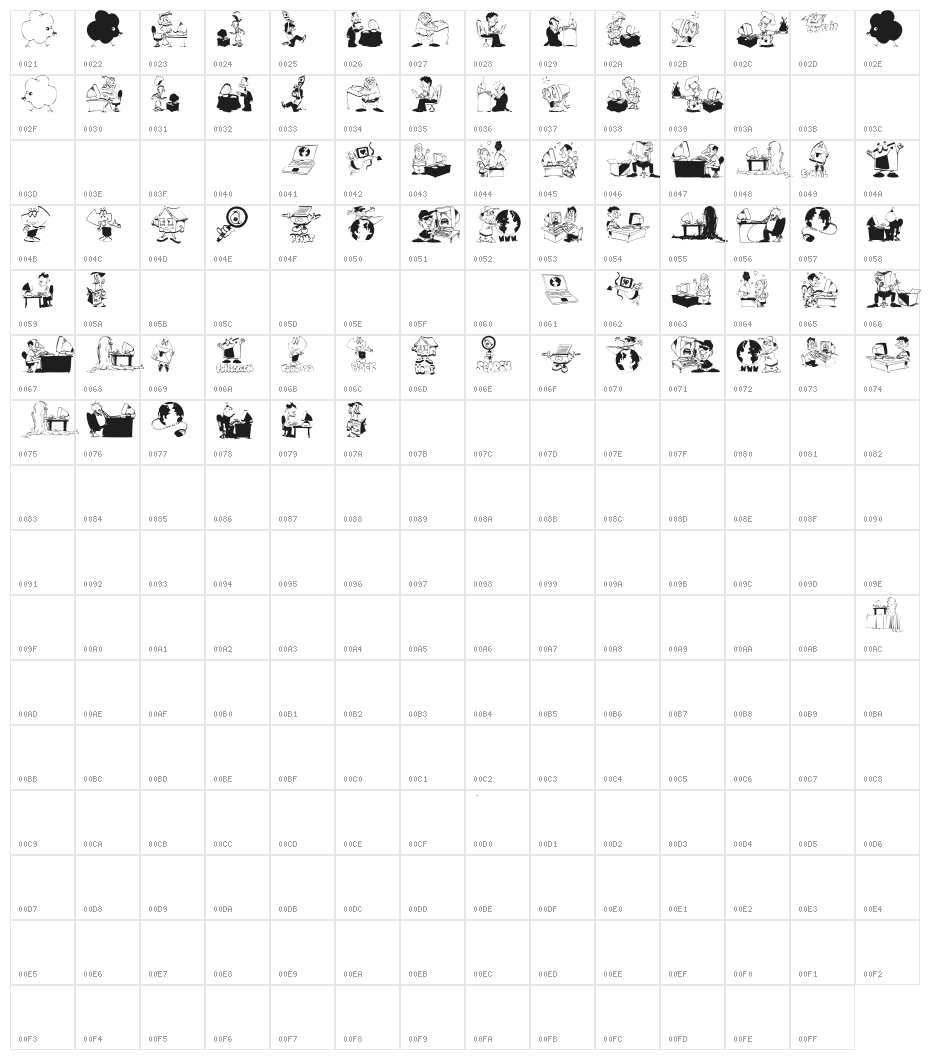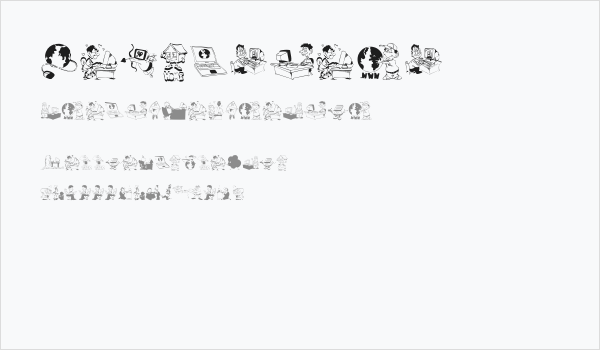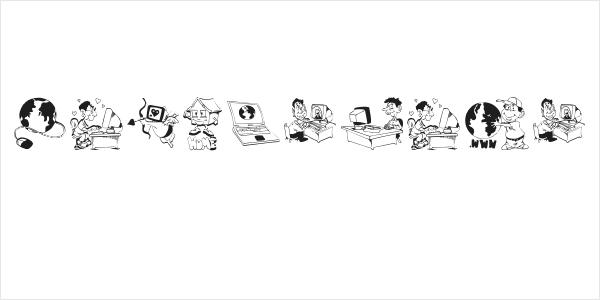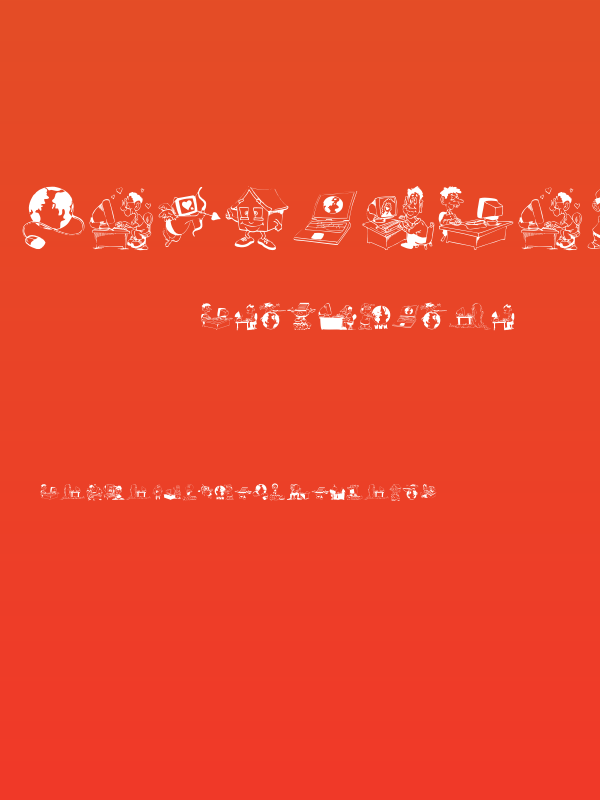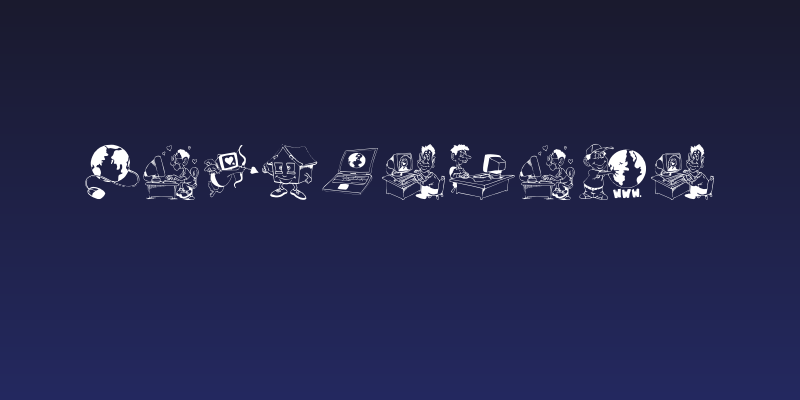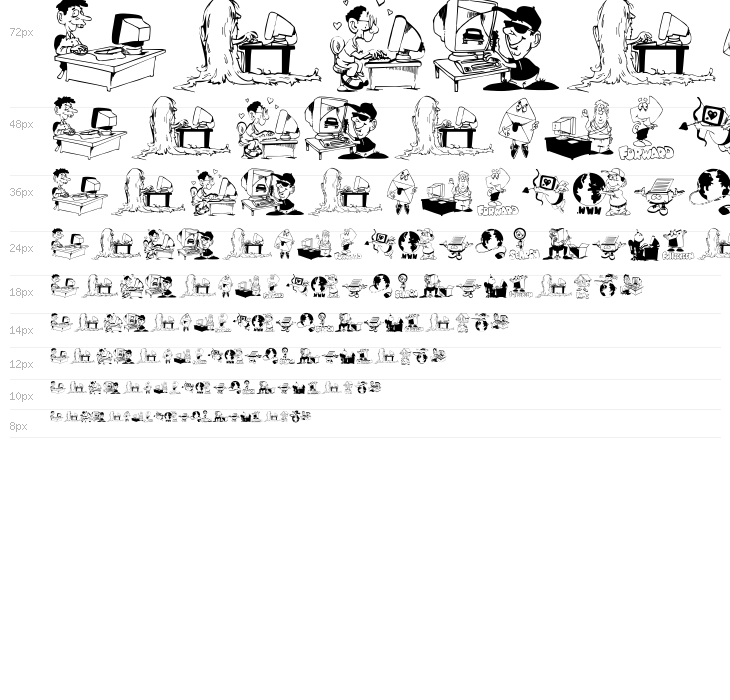
Webmasters Font
| Gesamtstil | Humorous, Playful |
| Anwendungsfall | Comics, Educational materials, Blogs |
| Vorgeschlagene Projekte | These illustrations could be used in educational materials, tech blogs, or as part of a comic strip series to add humor and engagement. |